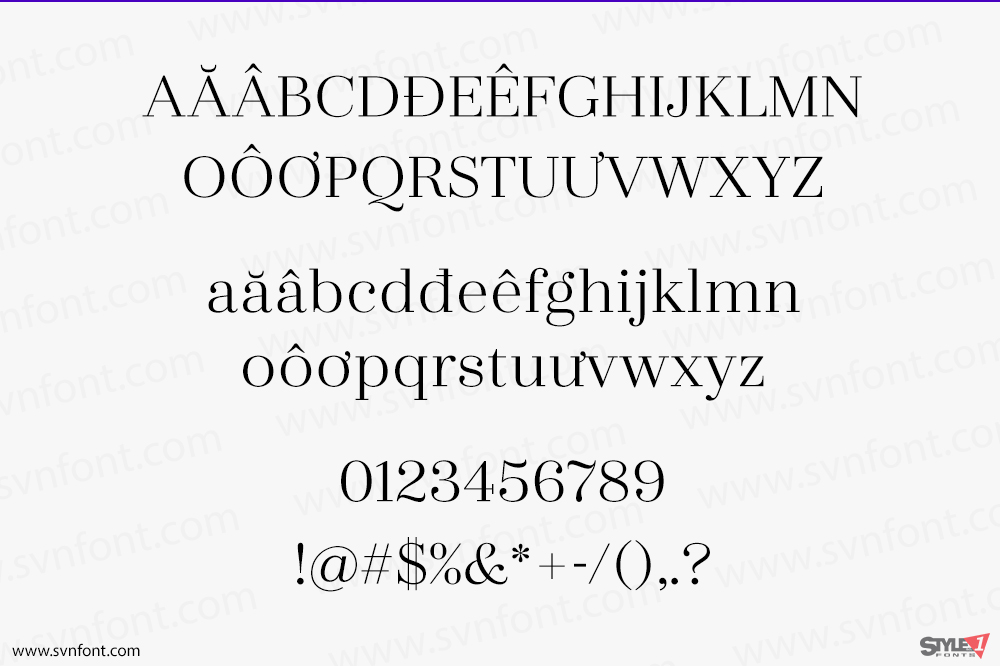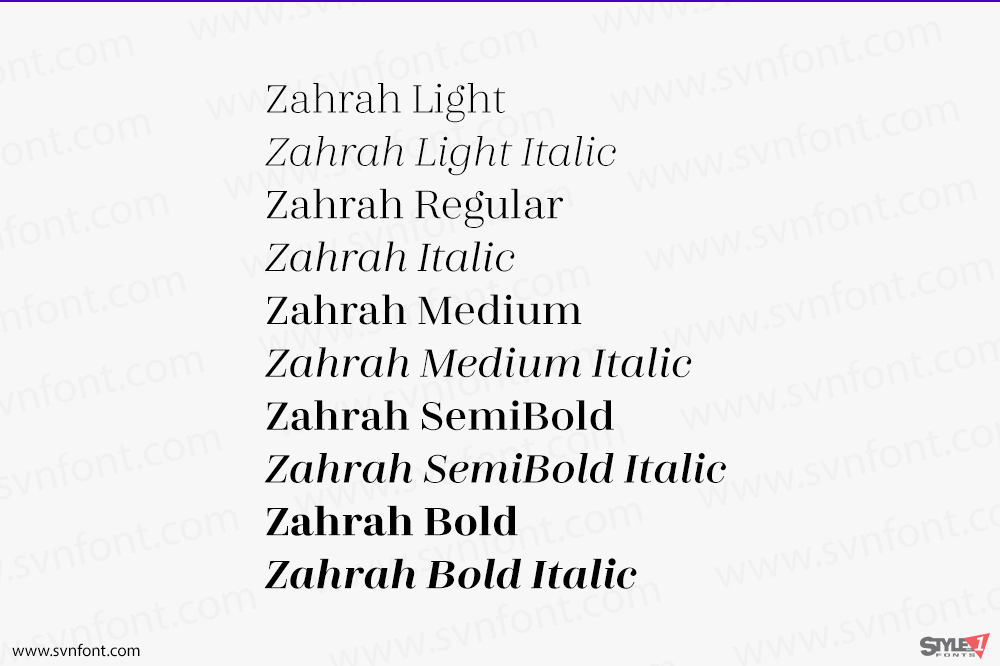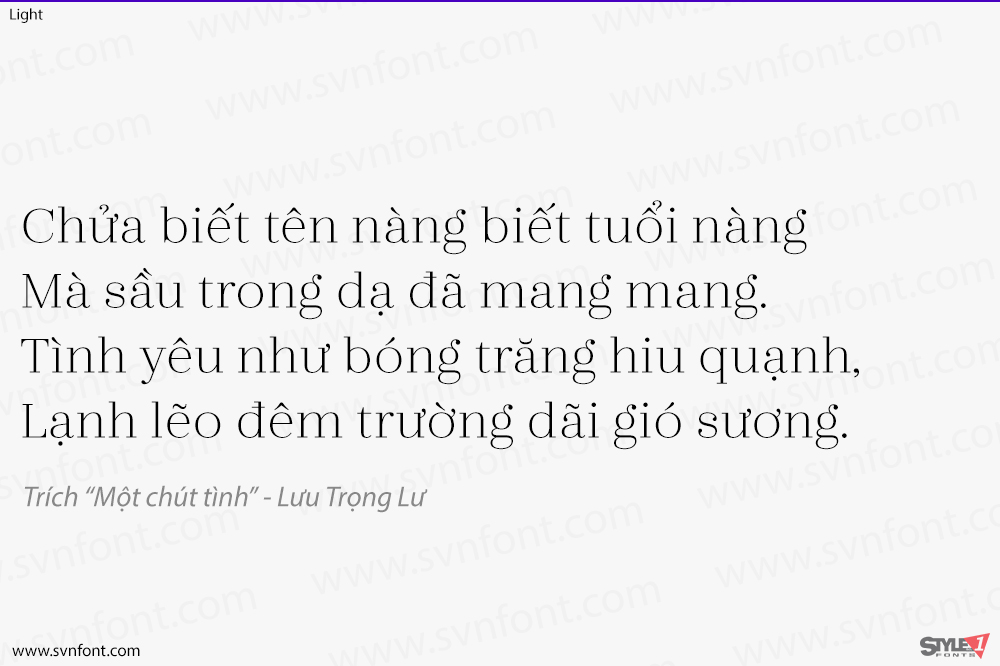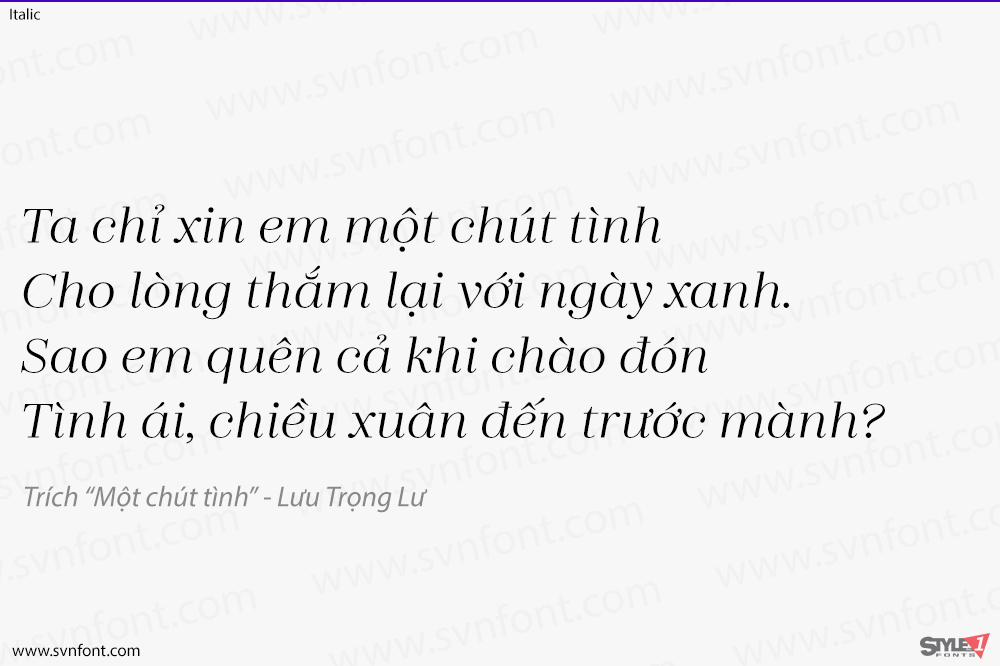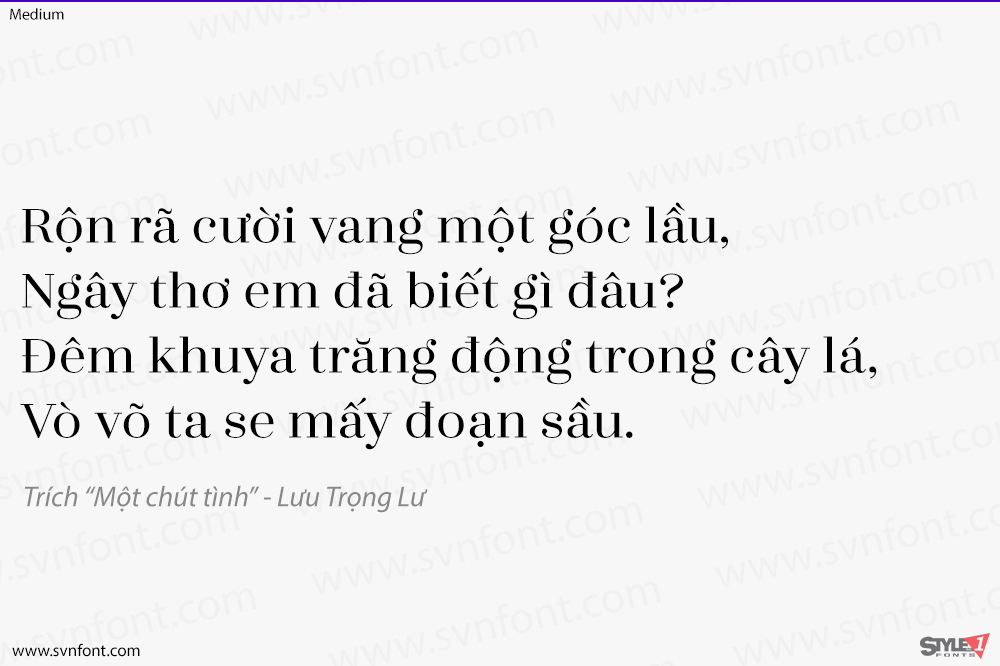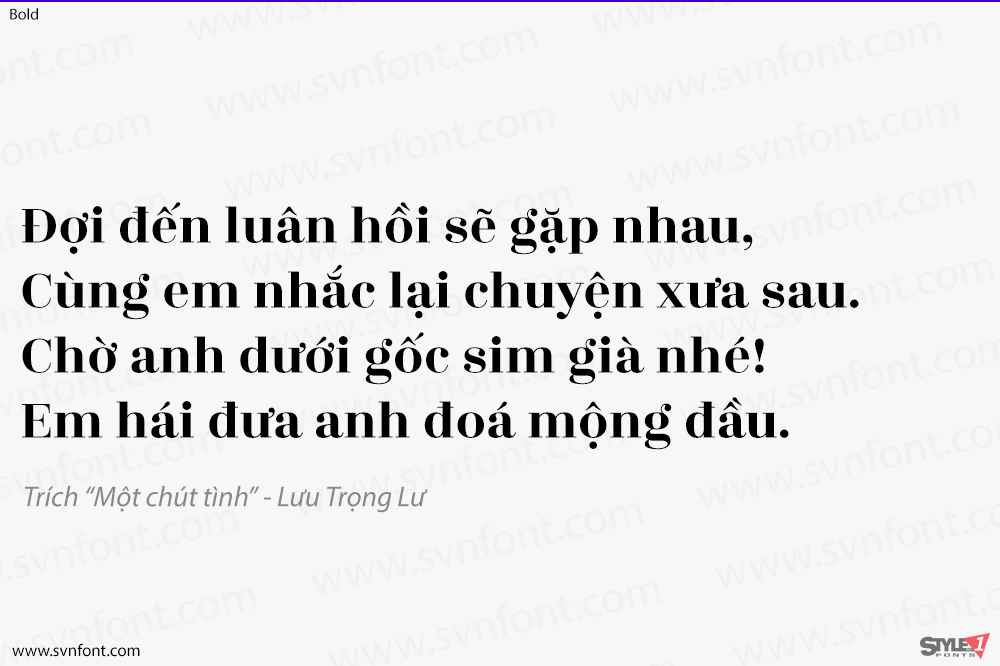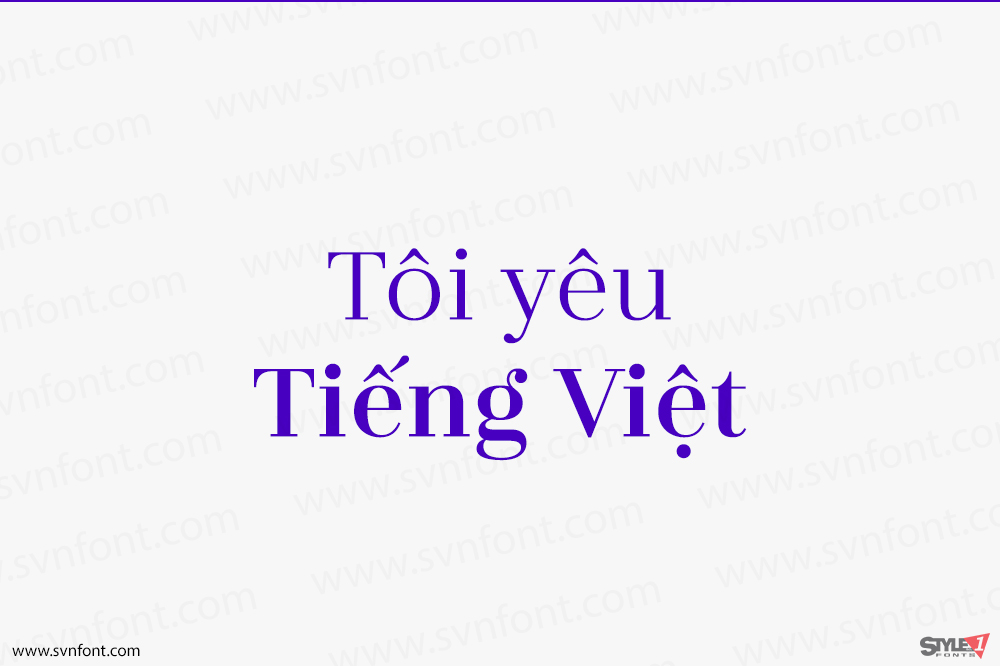
Kiểu chữ đa năng dành cho văn bản này, được thiết kế cho hệ chữ Latinh, đến từ Yoann Minet, một nhà thiết kế có trụ sở tại Paris. Nó bao gồm một vài chi tiết kỳ lạ, làm sinh động ngay cả những văn bản nghiêm túc nhất. Zahrah là một kiểu chữ serif theo phong cách Didone với mười kiểu: năm độ đậm thẳng đứng và các chữ nghiêng đi kèm. Các kiểu chữ Didone được đặc trưng bởi sự khác biệt thị giác mạnh mẽ giữa độ dày của nét đậm và nét thanh của chữ cái. Didone cũng có độ rõ ràng và sự đơn giản hóa hình học mà không thấy ở các kiểu chữ dựa trên các mẫu thời Phục hưng cổ hơn. Các kiểu chữ Didone được sử dụng cho nhiều ứng dụng khác nhau: từ nhãn mác thời trang hoặc mỹ phẩm đến văn bản báo chí, và từ các ấn phẩm học thuật đến báo cáo thường niên của các công ty thuộc Fortune 500. Chúng có thể được chọn cho hầu hết mọi thứ – và không có lý do gì chúng không nên định hình văn bản cho các trang web hoặc ứng dụng mới nhất của bạn.
Nhà thiết kế: Yoann Minet
Nhà phát hành: Indian Type Foundry